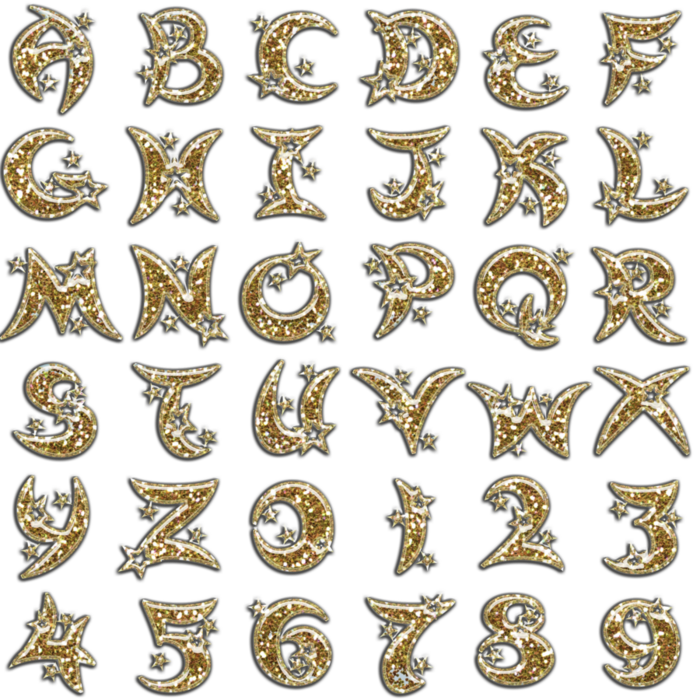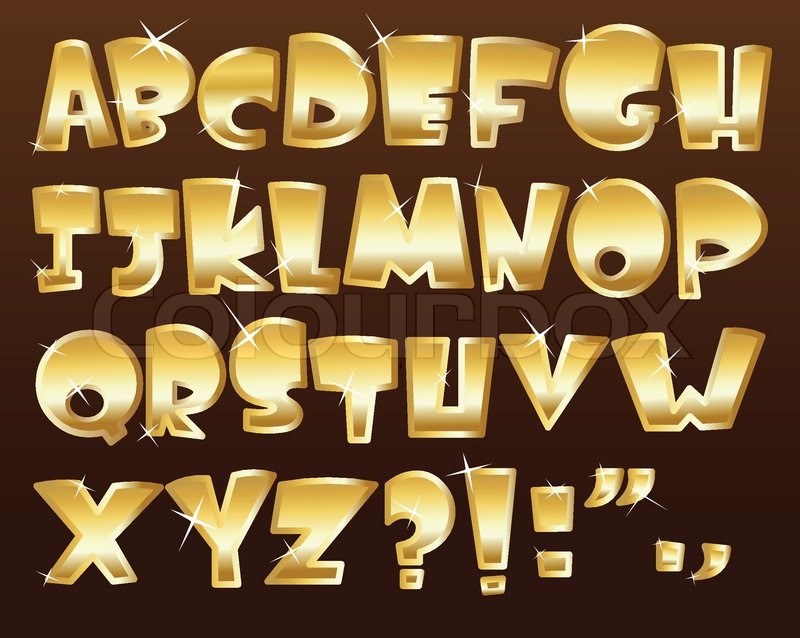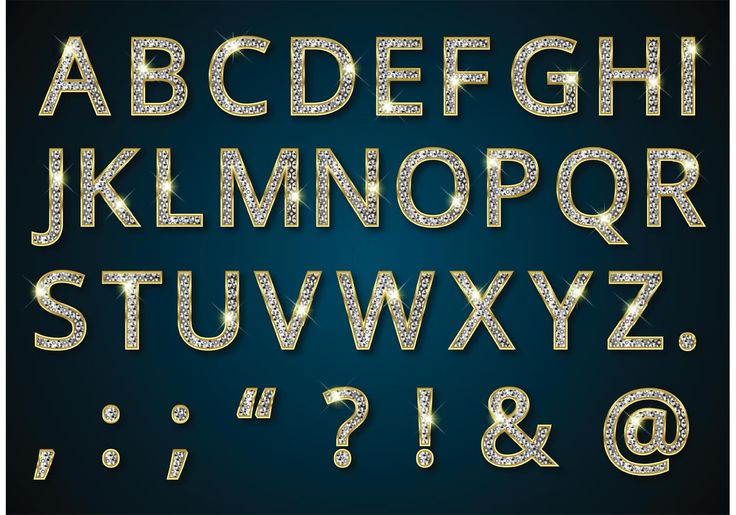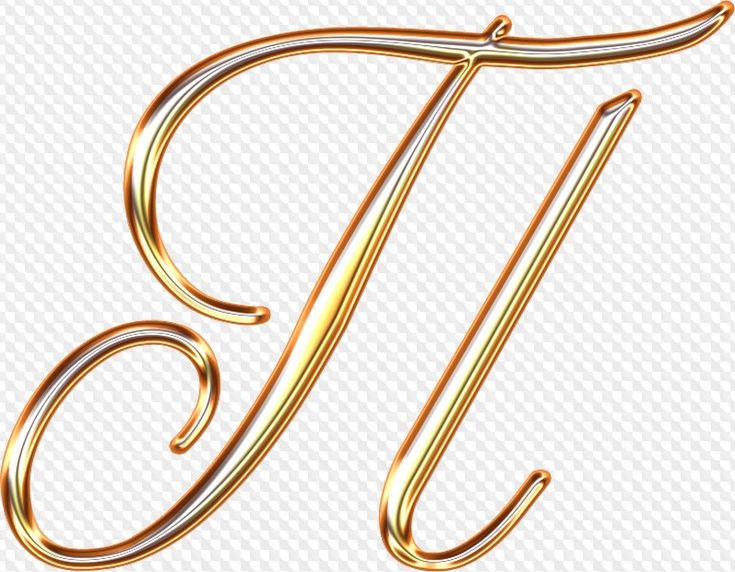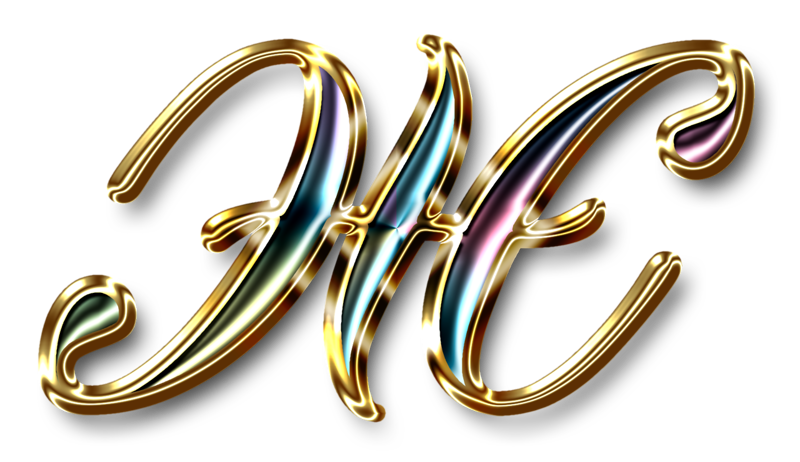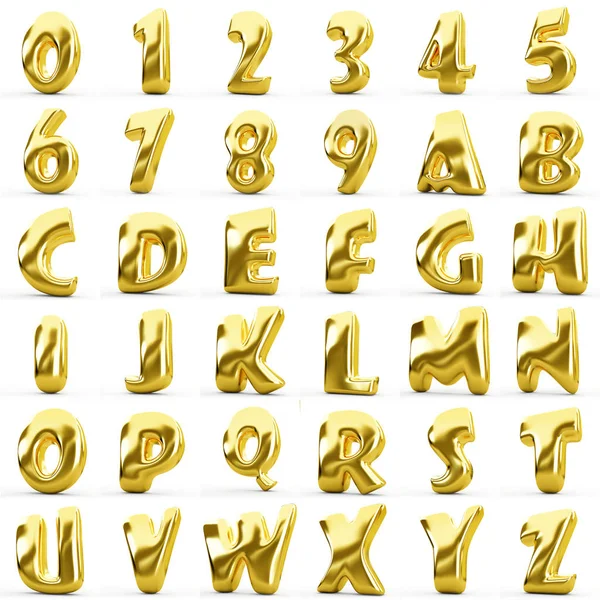
Золотой шрифт для фотошопа русский: Фотошоп шрифты — русские скачать бесплатно
77 золотых стилей для фотошопа
Вы можете создавать удивительные золотые текстовые эффекты, используя PSD-файлы со стилями слоев Photoshop и стили слоя ASL. Золотые стили имитируют, например, старое ржавое золото, старинное золото, золотые эффекты к праздникам. Благодаря именно желтому оттенку объект или текст приобретают более нарядный вид, они привлекают внимание, поэтому часто его используют для рекламы люксовых товаров или тех товаров, что имеют какую-то особенность.
Мы подобрали для вас несколько вариаций золотых стилей для фотошопа.
70 Golden Photoshop Layer Styles
Эти стили помогут вам добавить вашему художественному произведению эффект сияющего золота. Объект или текст, но они будут сиять, светиться, будто миллионы алмазов окрасили в оттенки желтого и оранжевого.
Gold Photoshop Layer Style
Простой, но красивый золотой стиль для Photoshop. Украсьте свои шрифты или графику этим стилем и выделите их! Стиль имитирует золотую краску, без объема для объекта.
80 Golden Styles For Photoshop
Стили Photoshop помогают дизайнерам выполнять работу быстро и легко. Эти 80 золотых стилей, которые вы можете использовать для написания заголовков, текста или для оформления объектов. Стили отличаются объемностью и сиянием, сочетания золотого с черным.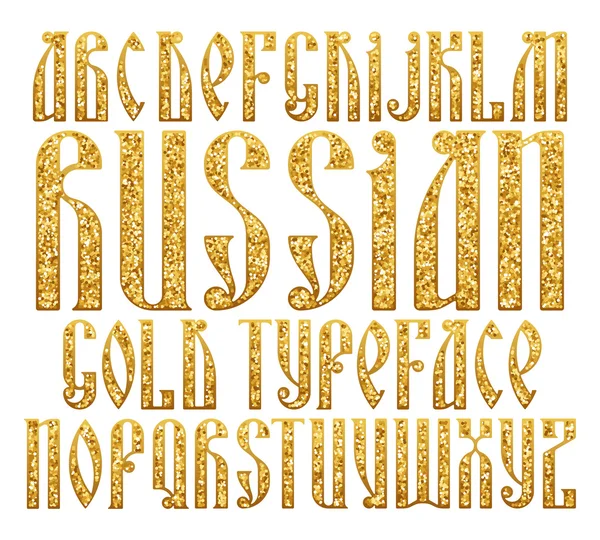
Elegant Gold Style
Создайте элегантную золотую типографику с помощью этого золотого стиля Photoshop. Внутри ZIP-файла вы найдете PSD с легкоредактируемыми смарт-объектами. Стиль «3D золото» работает для любого типа слоя: текста, векторной формы или растровых изображений.
Elegant Gold Effect PSD Mockup
Мокап PSD с глянцевым золотым текстовым эффектом. Используйте его для создания великолепных текстовых эффектов. Золотой текст редактируется, так что вы можете использовать любой тип шрифта, который вы хотите, любой текст, размер и т.д. Вы даже можете использовать его для фигур.
3D Gold Style
Стиль имитирует отчасти мульяшный вариант надписей, с небольшим сиянием. Файлы PSD имеют смарт-слои, поэтому с ними удобно работать.
Как сделать красивую надпись в фотошопе в стиле «леттеринг»?
Благодаря умению пользоваться различными инструментами фотошопа, можно буквально творить чудеса с текстом. В этом уроке подробно будет рассмотрено как сделать эффектные надписи в разных стилях.
В этом уроке создадим надпись в стиле Typography Lettering в виде наклейки в Photoshop CC.
В этом стиле используется один или несколько шрифтов, объединенных в единую сбалансированную картинку. Иногда за основу взят готовый текст, а иногда текст рисуется с нуля.
Выглядит такой текст очень модно и стильно. Поэтому приступайте с созданию своего стикера прямо сейчас.
Создание и размещение текста
В стиле «леттеринг» русские слова используются намного реже английских.
Почему? Одна из причин это разница в начертании букв, русские буквы ровнее и в верхней части редко выступают за пределы строки.
Поэтому даже при использовании соответствующего шрифта русские слова не будут так красиво выглядеть и нуждаются в дополнительной прорисовке.
Мы рассмотрим самый простой способ. Возьмем за основу готовый шрифт, подходящий для этого.
Напишем три слова «don’t give up» на отдельных слоях, как показано на рисунке ниже:
Теперь надписи нужно так масштабировать и развернуть, чтобы не оставалось больших пустых мест между словами и слова читались в правильной последовательности.
Возможно, отдельные буквы или части букв придется подправить. Для этого переведите их в форму, нажмите правой кнопкой мыши по слою и выберите «Convеrt to Shape».
Затем, с помощью инструмента «Прямое выделение» вы сможете отредактировать форму букв.
Наложение эффектов
Когда форма готова наложите на текст эффекты: градиентная заливка и обводка. Я поставил желто-оранжевый градиент и черную обводку.